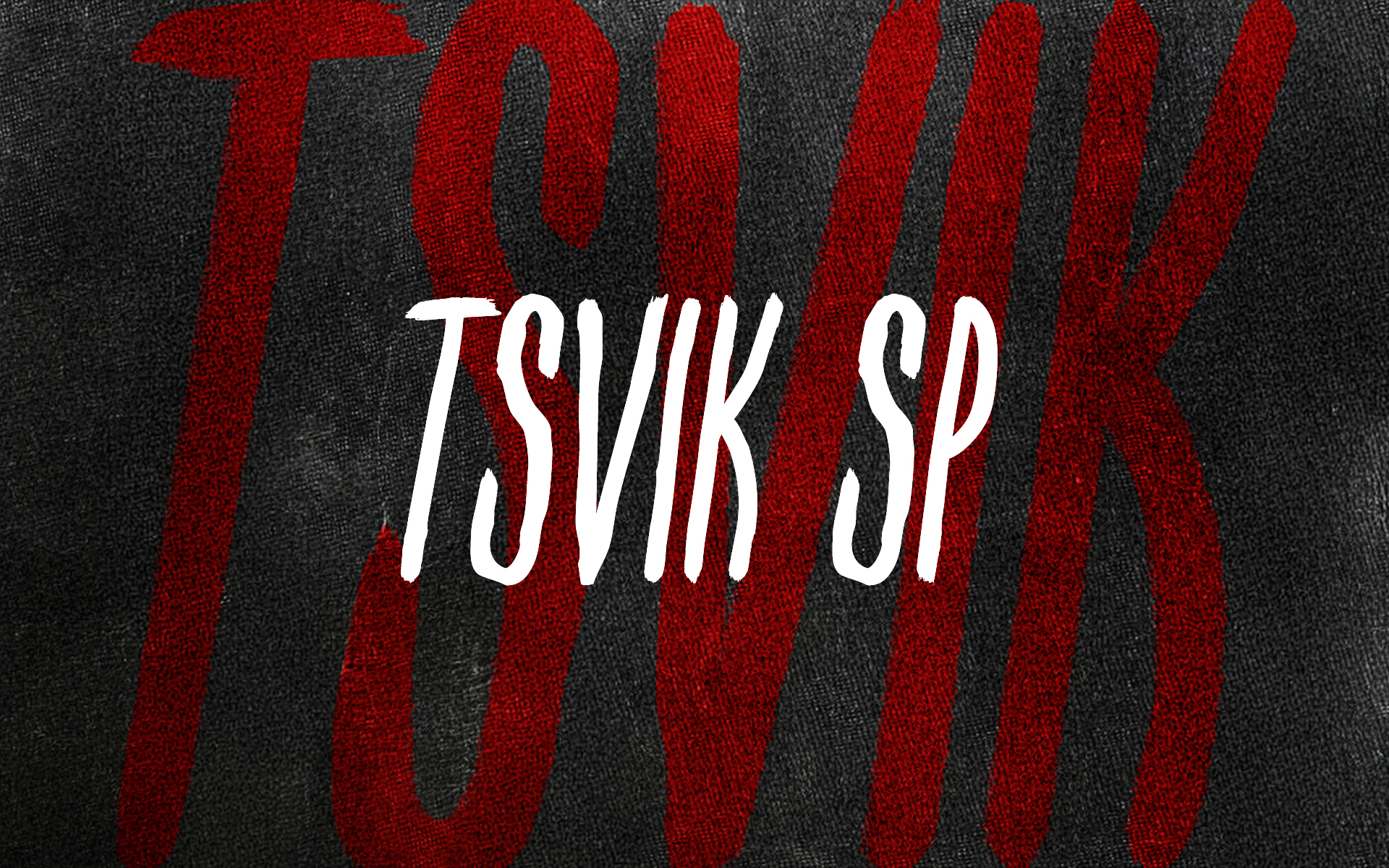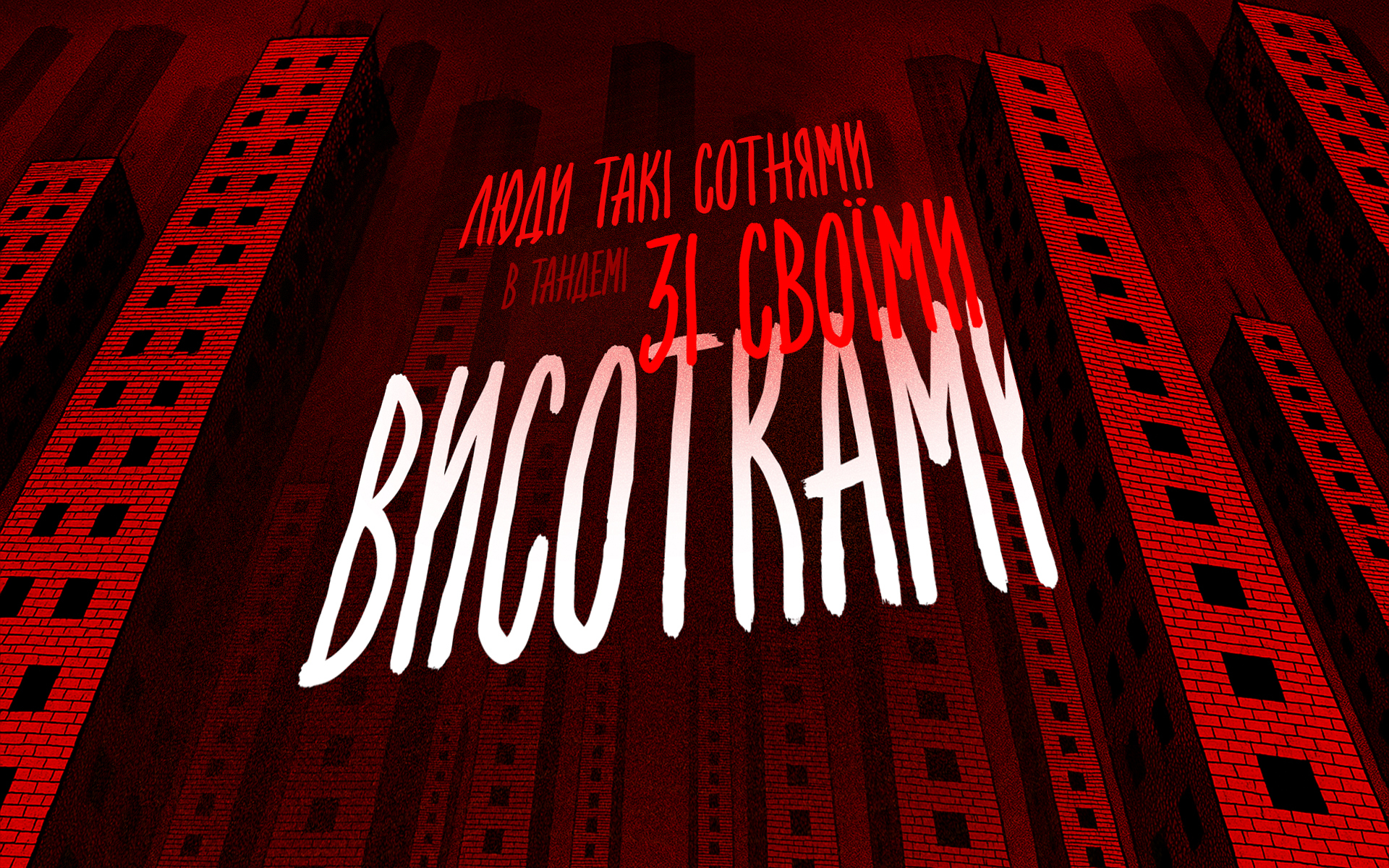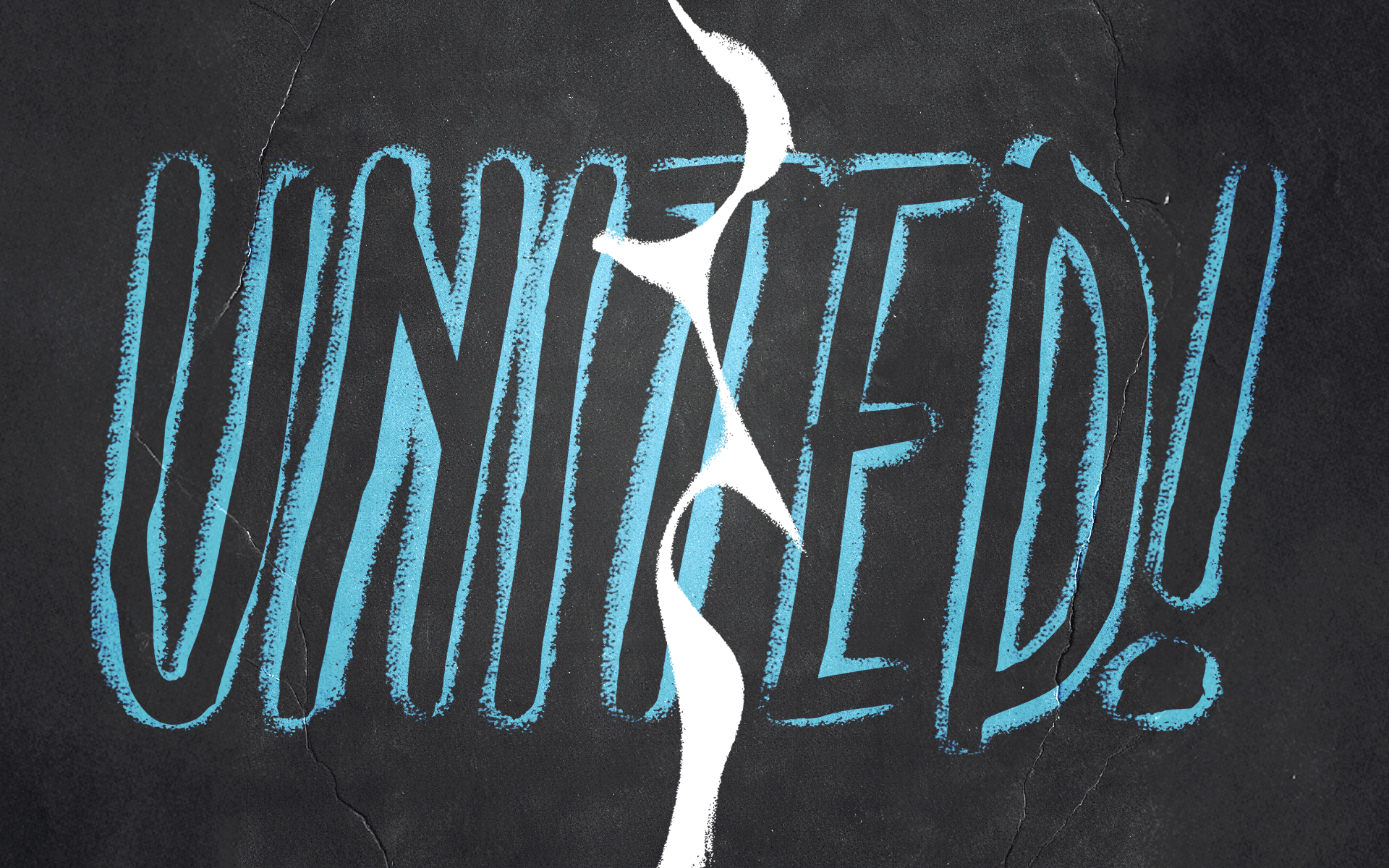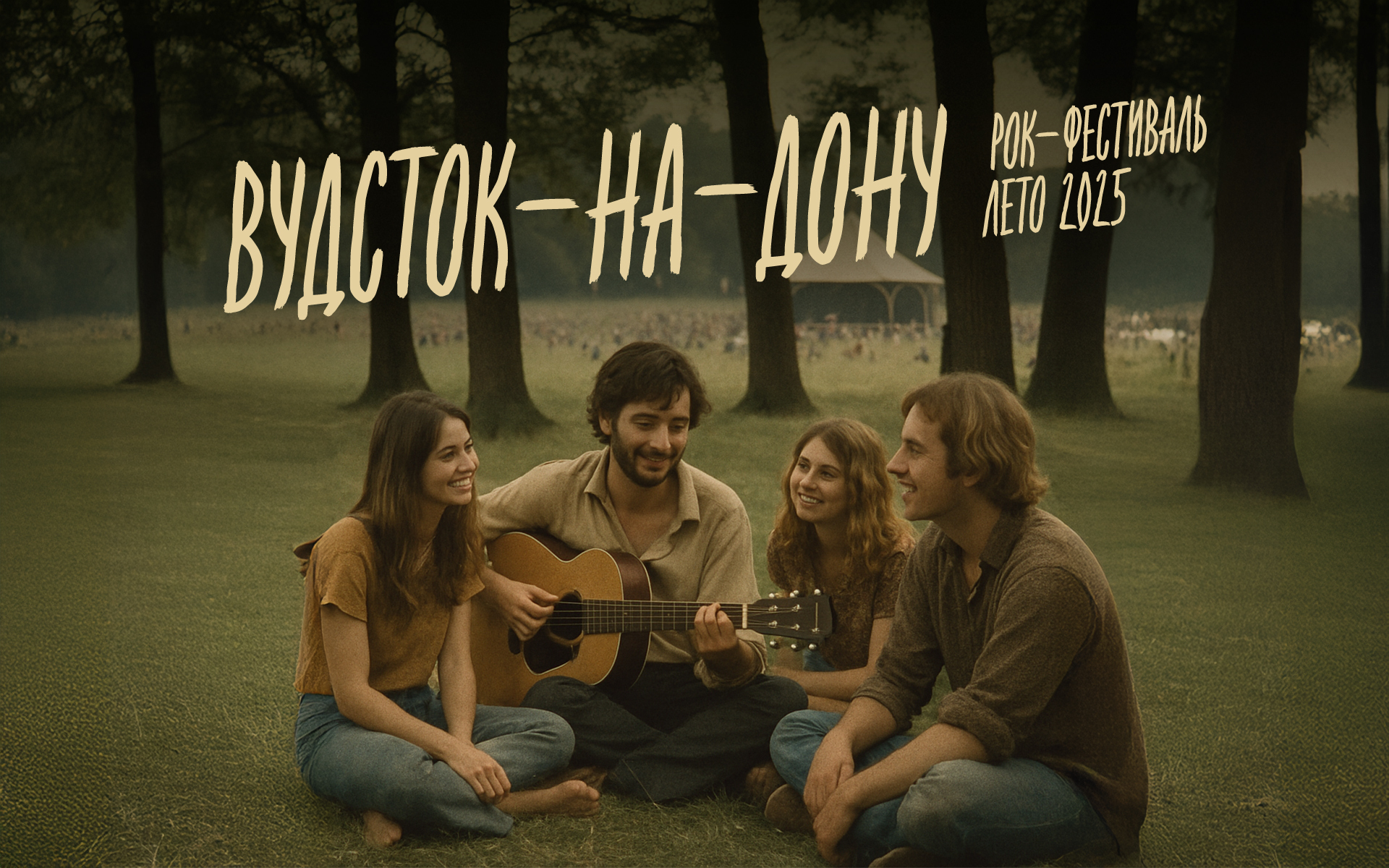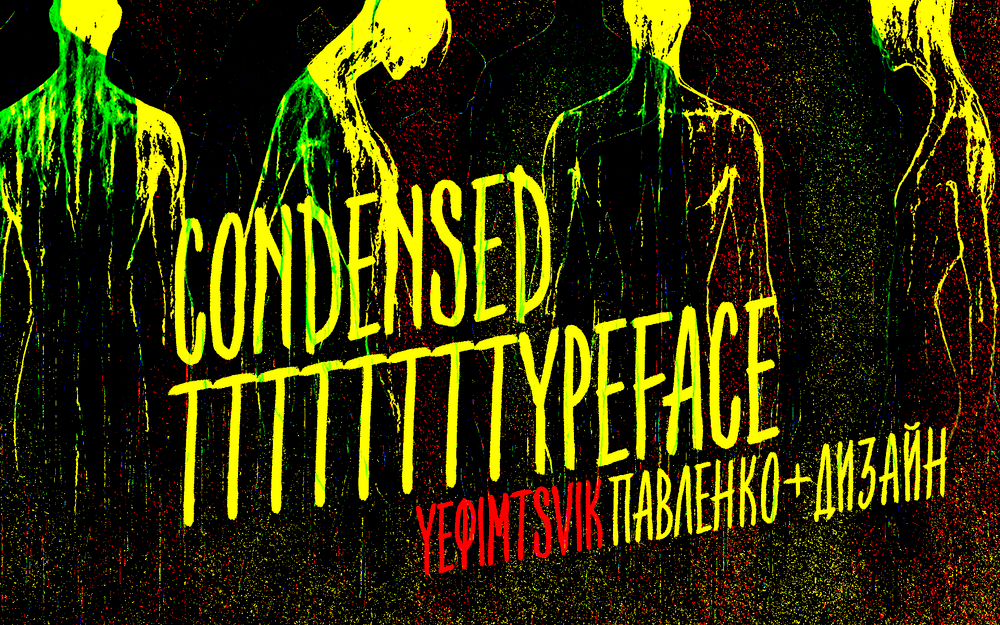
Шрифт Цвик
Tsvik — выразительный рисунок, отсылающий к плакату Ефима Цвика «Не дадим повториться!». Строка выглядит написанной кистью на транспаранте: рваный контур, перепады масштаба, живая динамика и намеренно оставленный след спешки. Отсюда и задачи — музыкальные афиши, зиновая и самиздатовская графика, айдентика и арт-проекты с социальным или бунтарским посылом. В комплекте — полная версия STAR и лицензия.